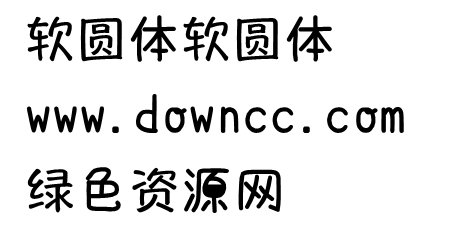
軟圓體是暖色君推出的一款個(gè)性pop字體,字形姣好而圓潤,給人十分活潑生趣的視覺體驗(yàn),讓你的設(shè)計(jì)文字更顯得大方簡潔,喜歡的朋友就來綠色資源網(wǎng)體驗(yàn)吧!
軟圓體軟圓字體以其獨(dú)特的手寫風(fēng)格和俏皮的樣式而廣受歡迎,充滿了青春活潑的氣息,適合年輕人在手機(jī)上使用。
軟圓體是暖色君在文泉驛微米黑體字體的基礎(chǔ)上改小而來的藝術(shù)字體,線條細(xì)膩,符號(hào)突出,自帶加黑讓文字更加顯眼,給你的平面設(shè)計(jì)、包裝設(shè)計(jì)增添更多光彩!